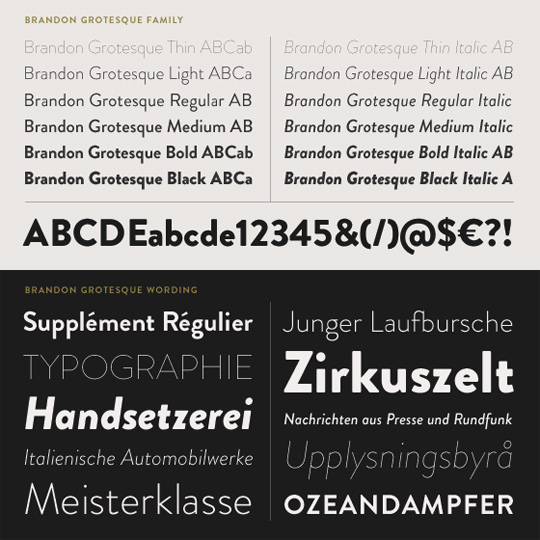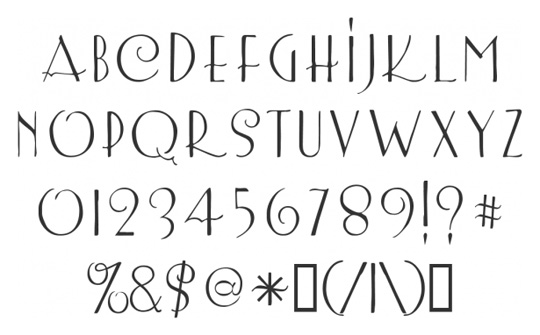
Typographie retro à télécharger
L’utilisation d’un style rétro ou «vintage» a pour but de transporter votre audience dans une décennie antérieur. Pour arriver à créer l’ambiance d’autre-fois, les designeurs utilisent différentes textures et différents patterns. Cependant, il est important également de bien choisir sa typographie retro qui saura représenter l’époque choisie pour votre design graphique ou web.
Dans ce billet, vous trouverez 30 excellentes typographies retro et vintage qui pourront vous être utiles pour vos designs. Vous noterez probablement que les polices de caractères choisies se rapportent aux années 1920 jusqu’aux années 50.